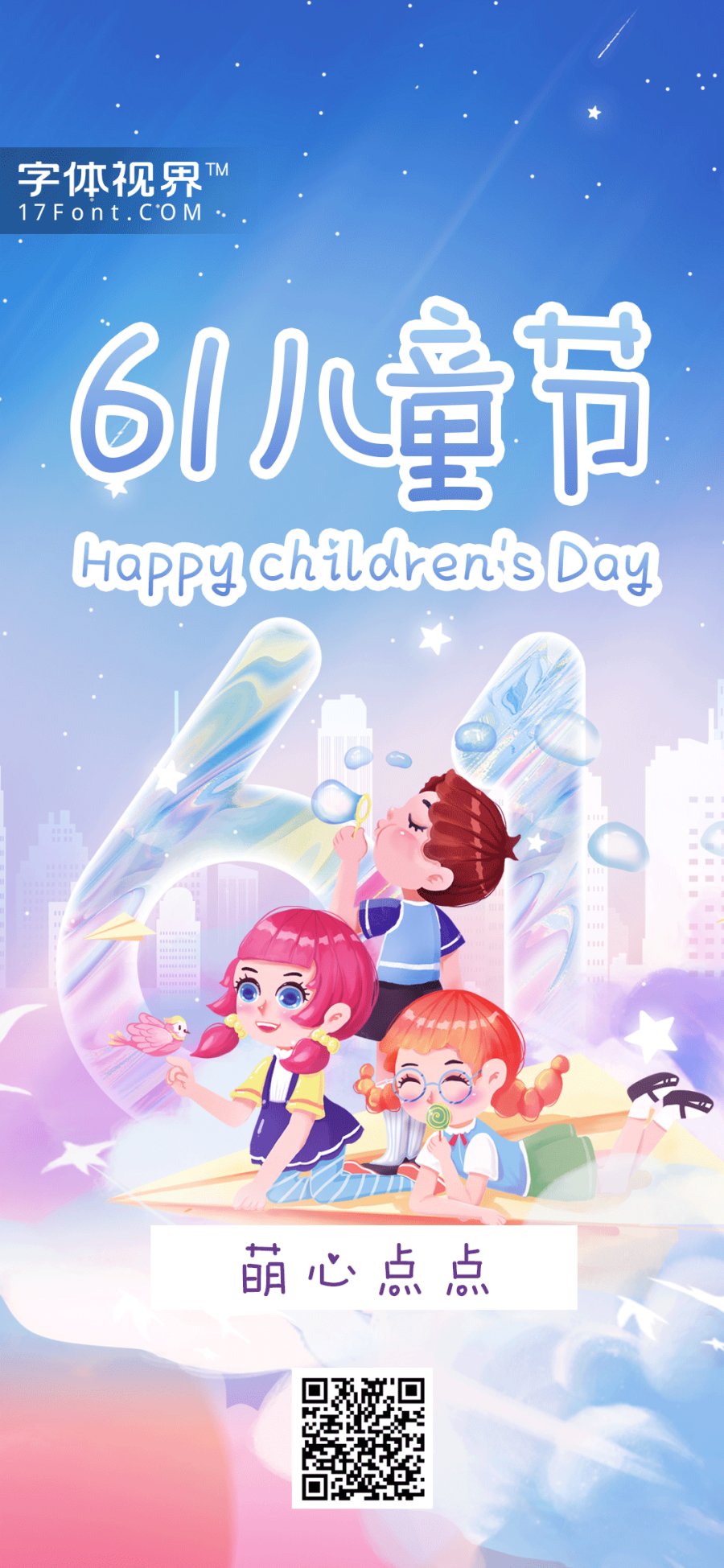
岁月永远年轻,我们慢慢老去,你会发现,童心未泯,是一件值得骄傲的事情。小时候,眼里的东西都是新的,我们对这个世界充满了好奇 ,我们不愿停歇的去探索这个世界。萌心点点带你一起探索这个世界的美妙。
萌心点点是一款活泼可爱字体,字笔画简单直接,没有弧线笔画完全用直线组成整个字体,结构多变,有趣中带着一下坚实和可爱。